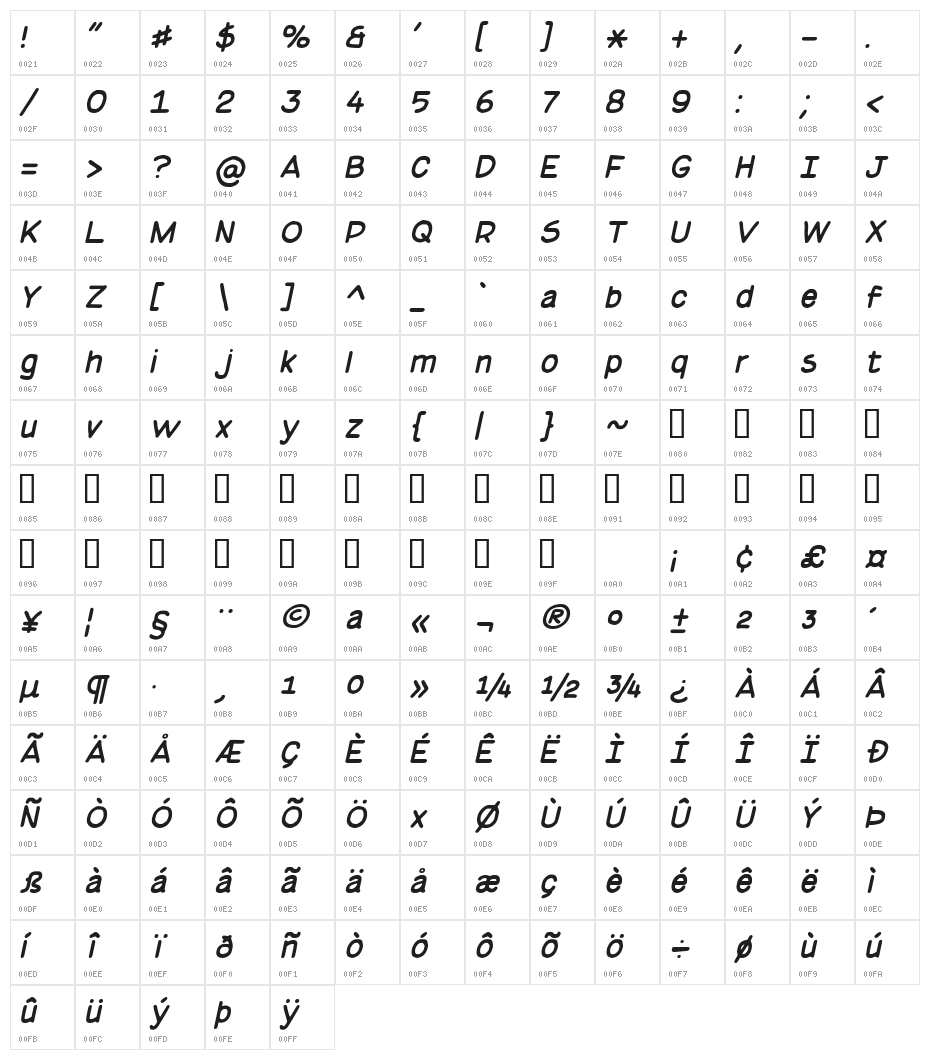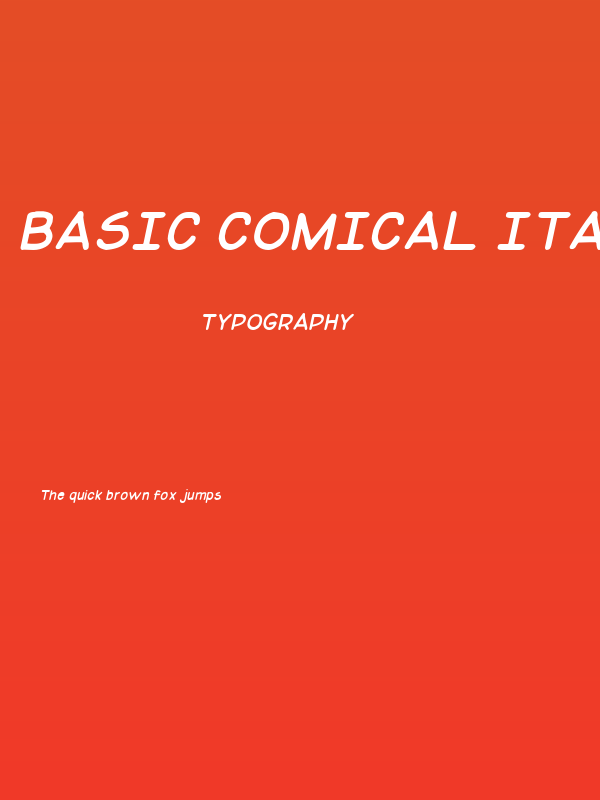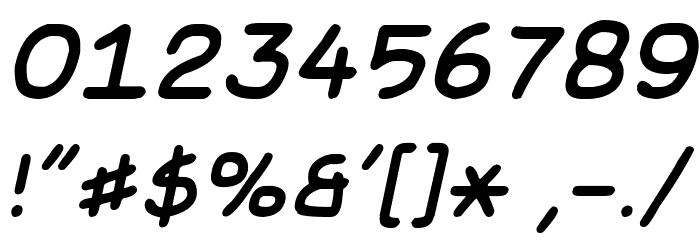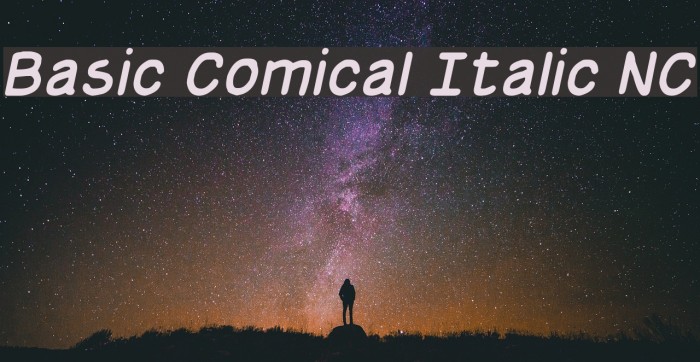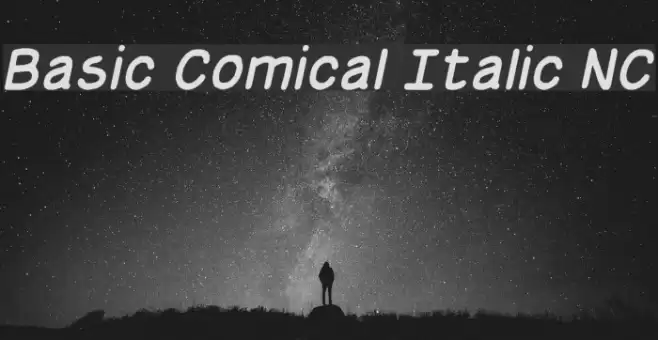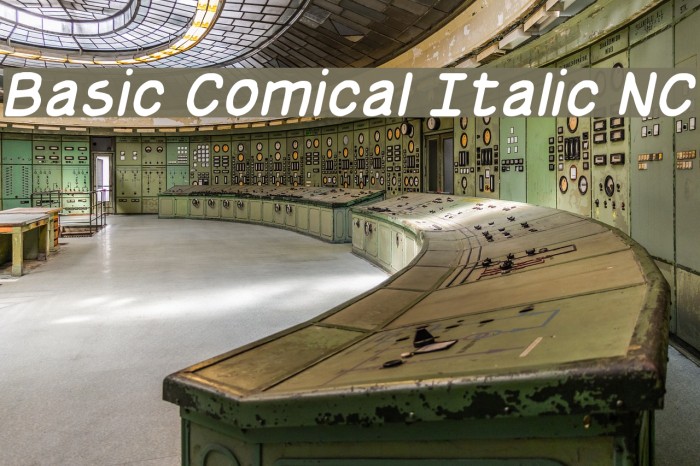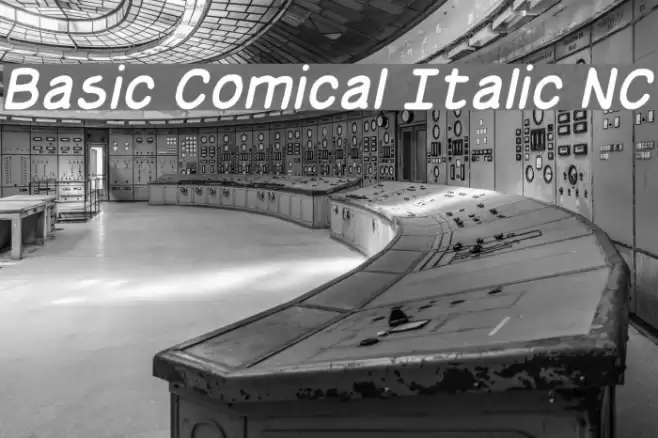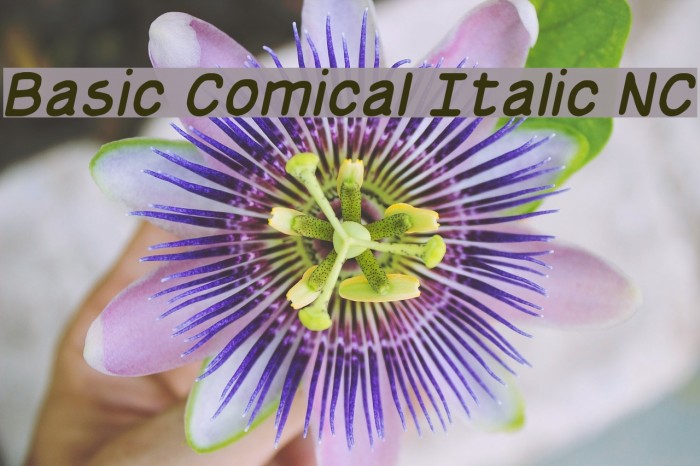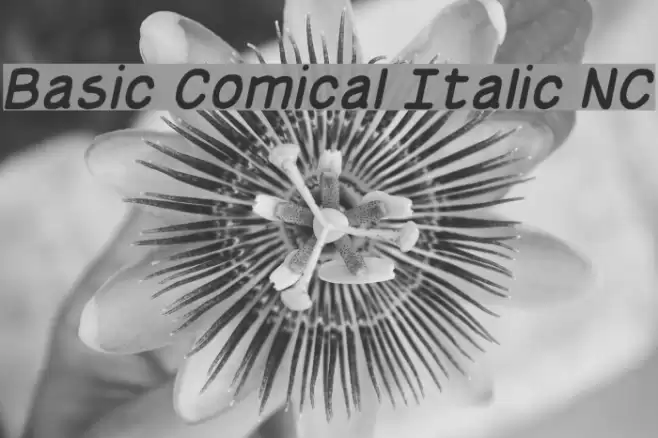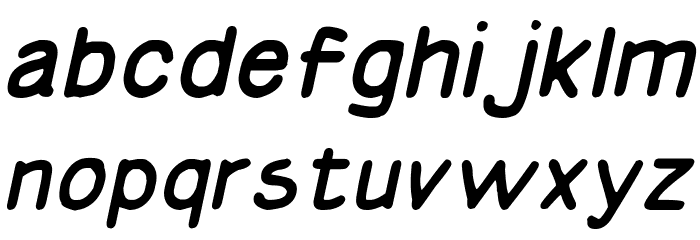
Basic Comical Italic NC Font
✎ Comic
| Kategorien | Comic |
| Gesamtstil | Playful |
| Anwendungsfall | Headlines, Logos, Informal Text |
| Vorgeschlagene Projekte | Ideal for comic books, children's books, playful branding, and informal invitations. |